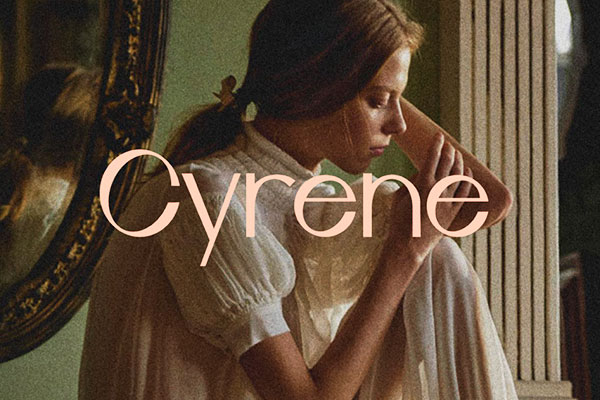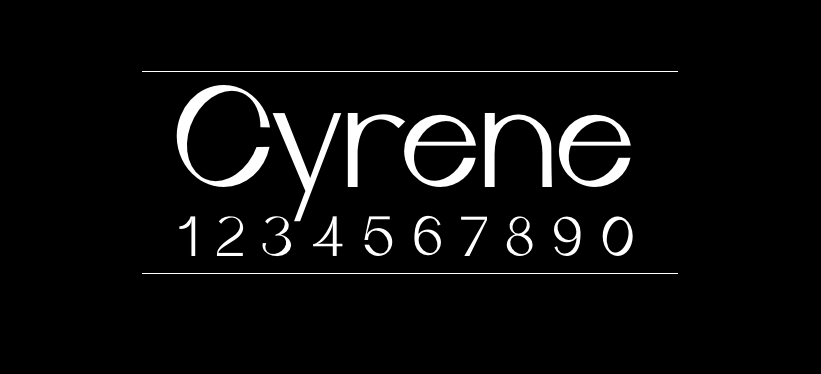
Cyrene
Cyrene字体介绍
Cyrene是加拿大设计师Riccardo Agostinelli创作的英文字体。Cyrene是一种免费的,优雅的Sans Serif字体,具有一流且精致的风格,非常适合品牌,海报,杂志,徽标,标题等。 该字体首发于Behance,作者声明个人及商业使用免费。
Cyrene字体应用示例